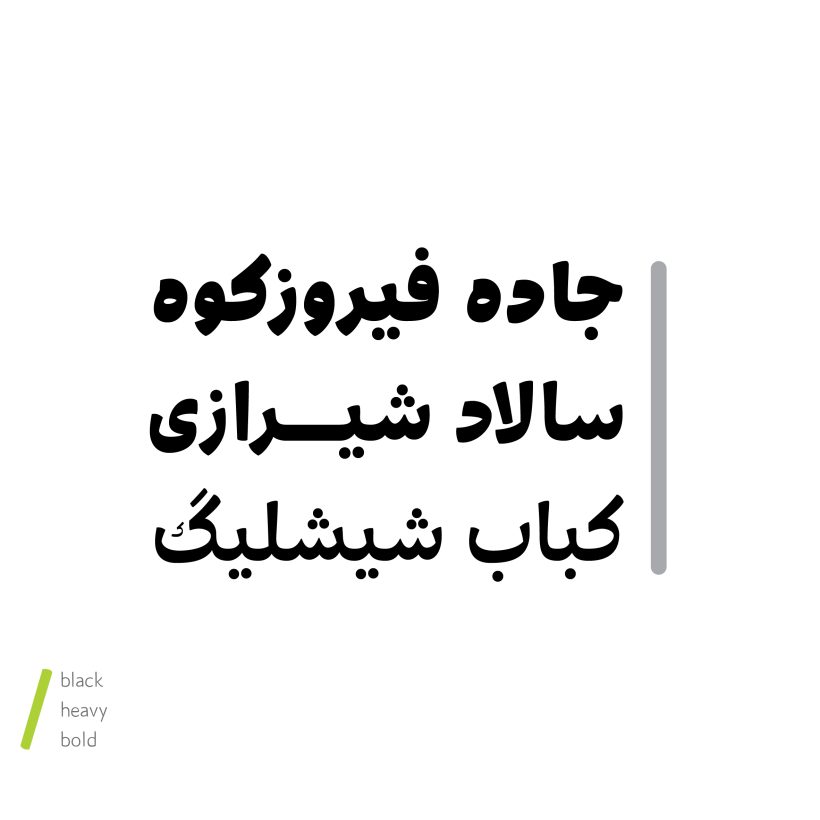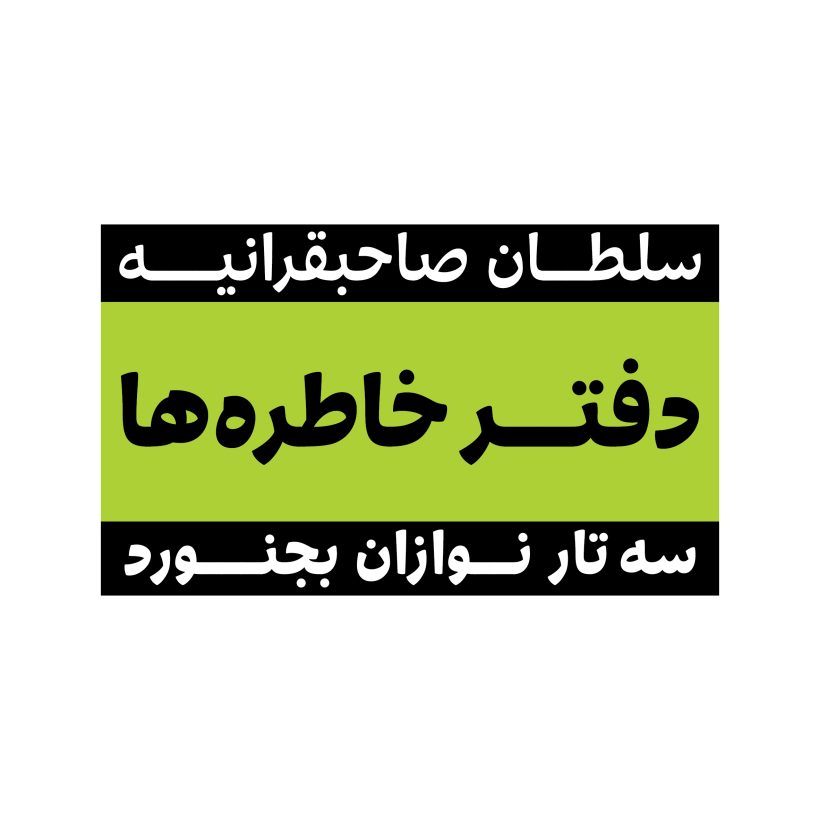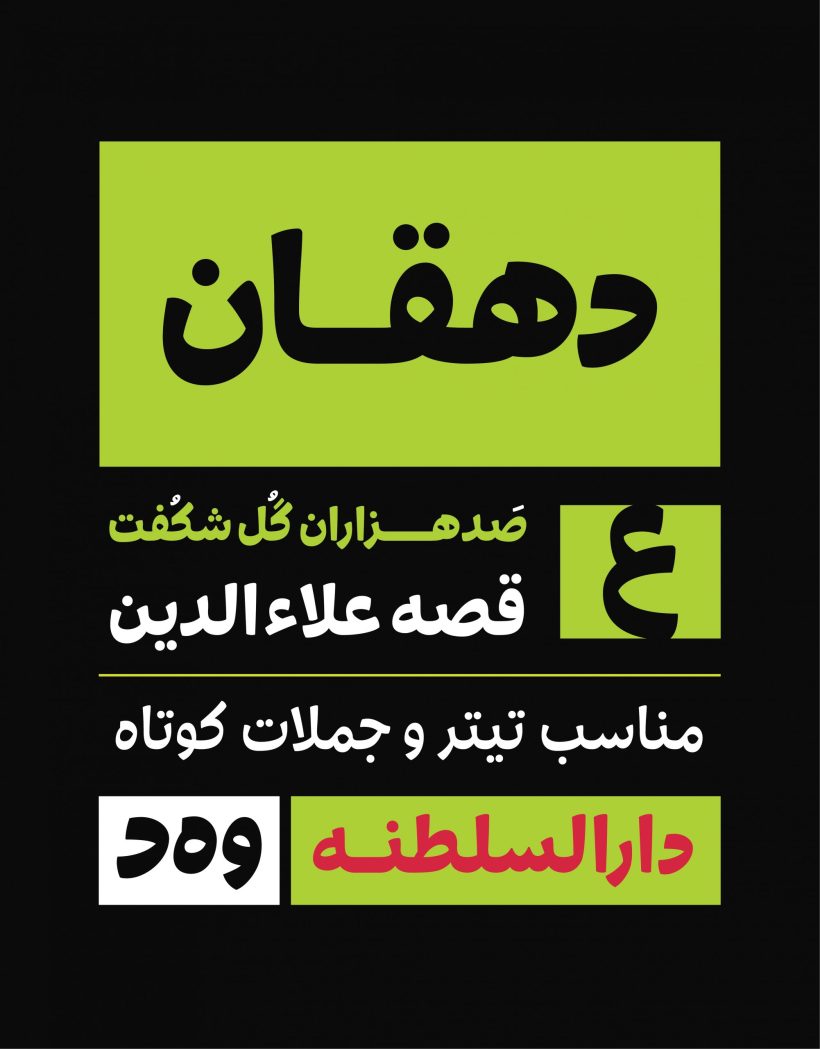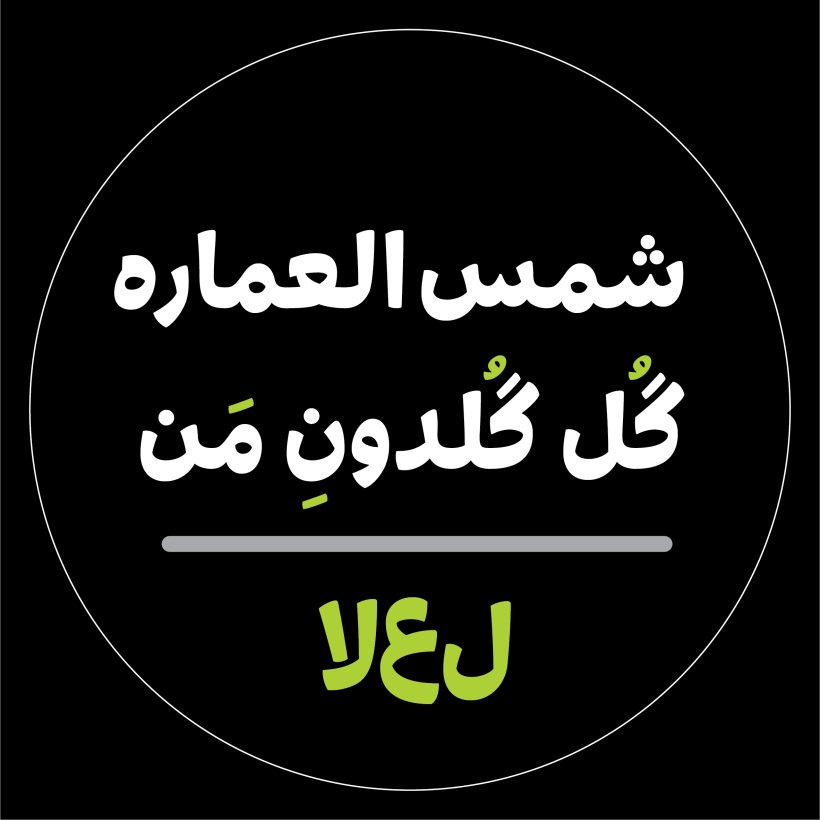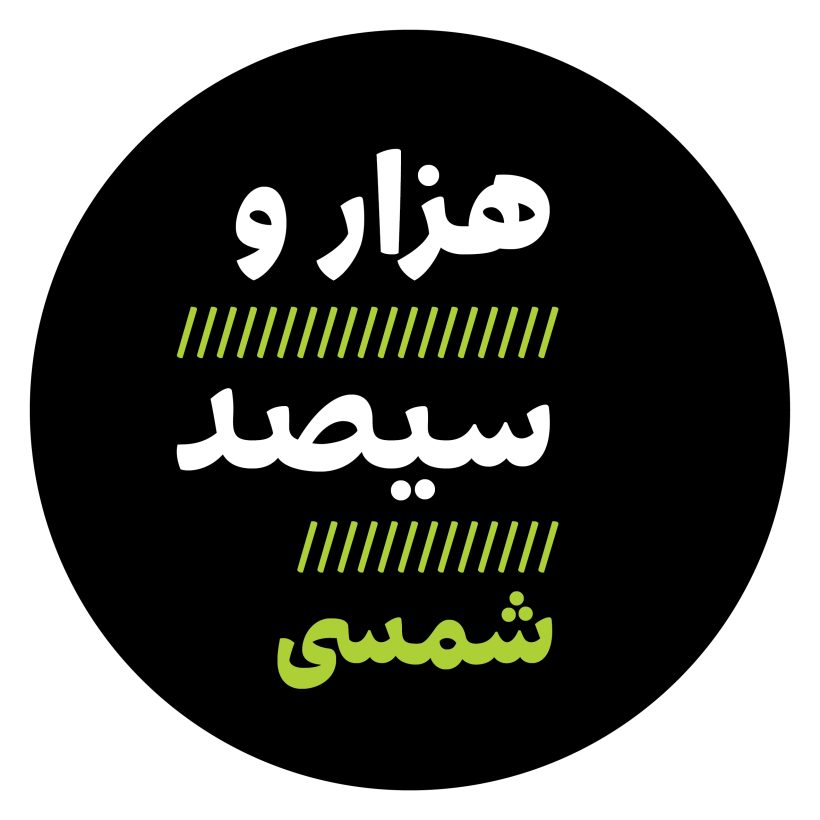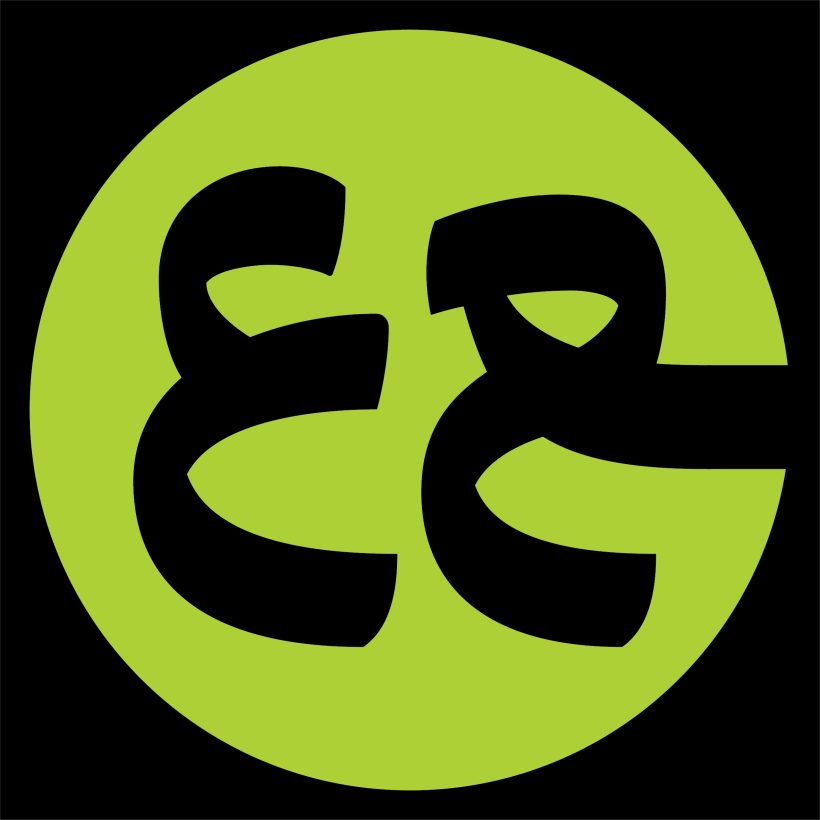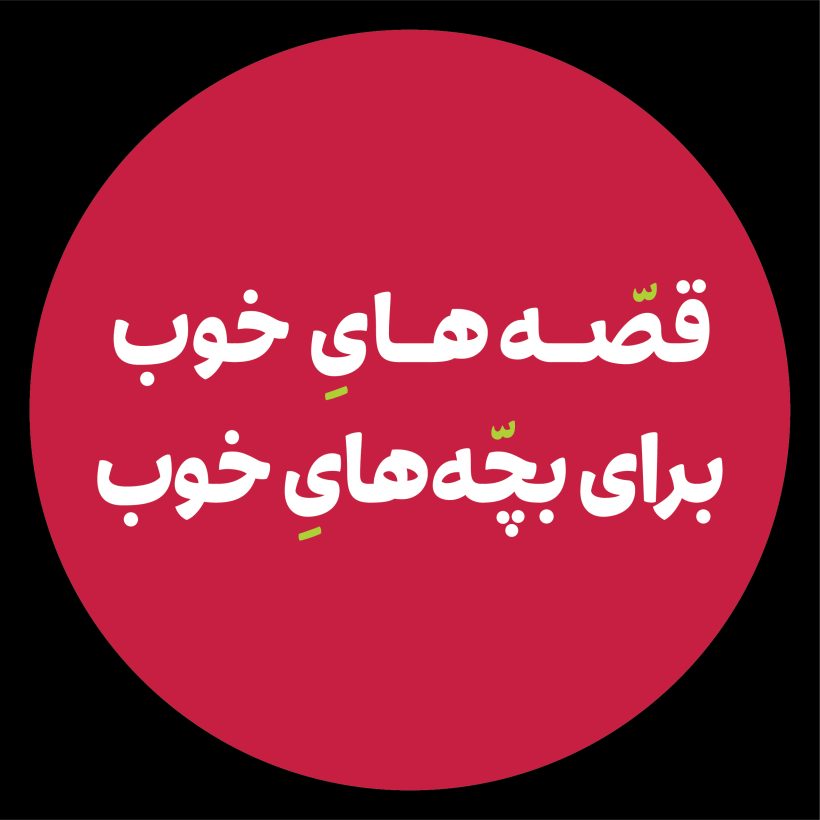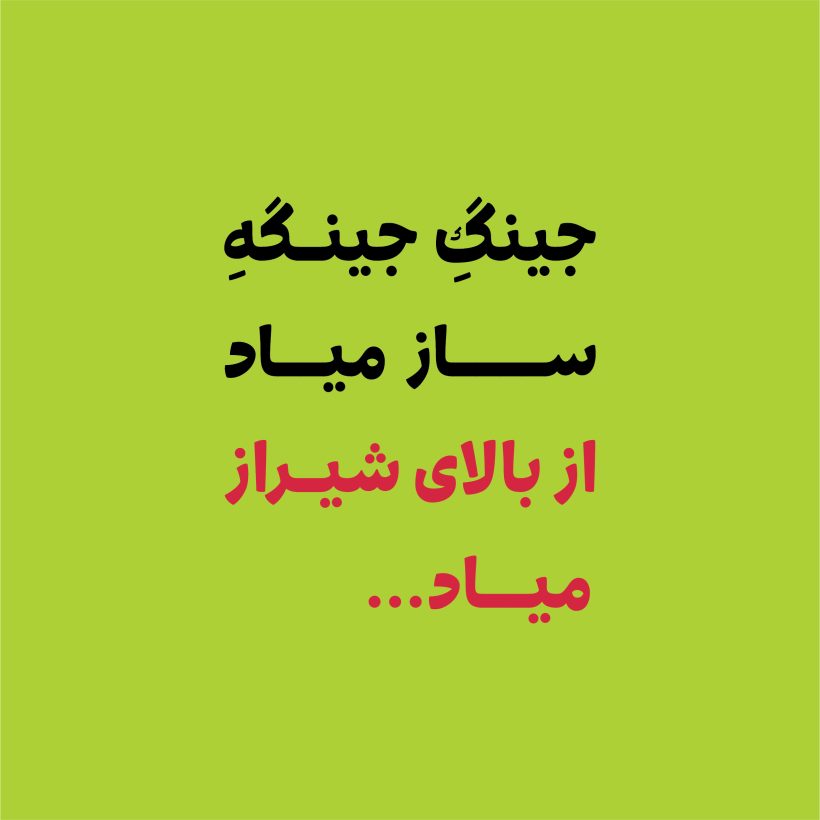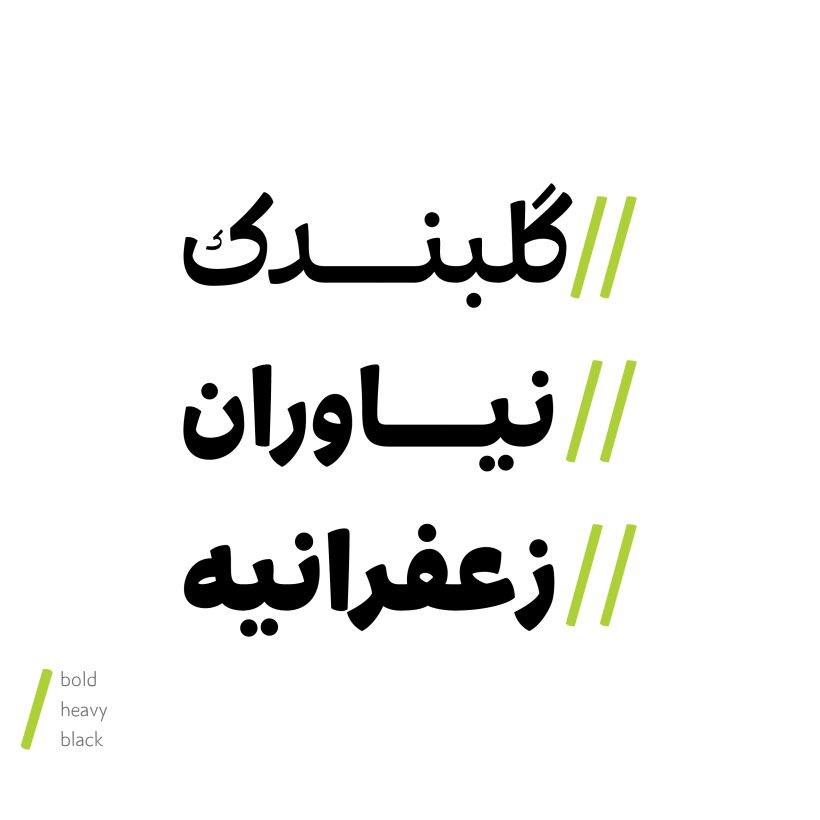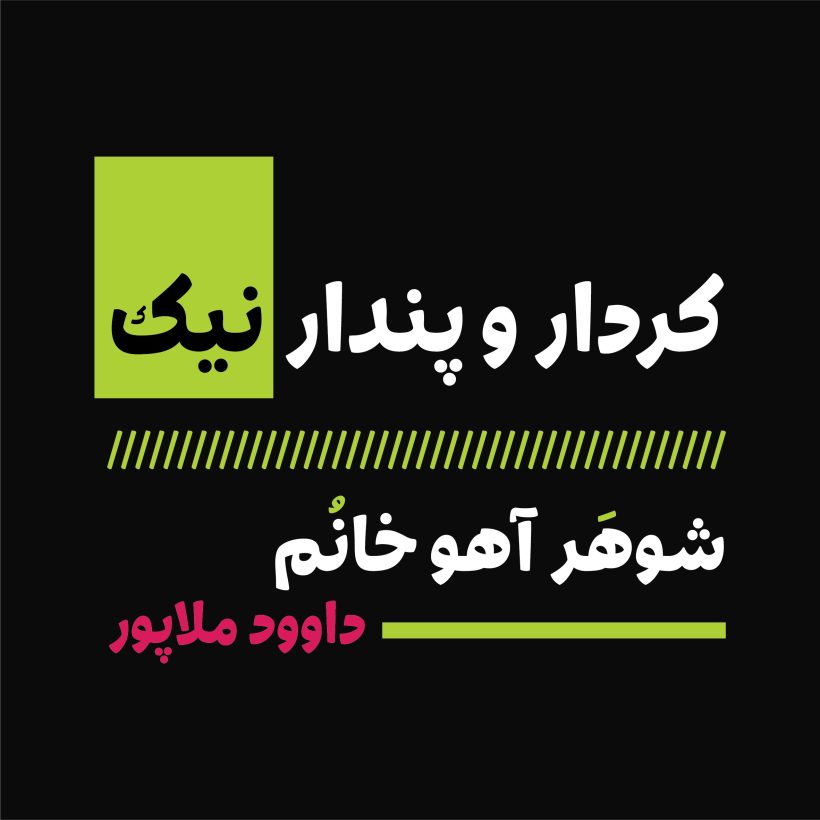
خانواده فونت دهقان
فونت دهقان با الهام از خط سکه های کهن و با لحنی صمیمی و عامیانه طراحی شده است.
دهقان فونت نمایشی، متمایز و در سه وزن bold / heavy / black طراحی و اجرا شده است. در این فونت حروف با دور بیشتری طراحی شده است و لحنی صمیمی و دوست داشتنی دارد و برای تولید محتوا و موضوعات و قصه های عامیانه مناسب به نظر می رسد.
در فونت دهقان قواعد کرنینگ و اعراب‌گذاری به طور کامل رعایت شده است. همچنین دهقان دارای لیگیچر و کاراکترهای جایگزین می‌باشد و این امکان را به مخاطب می‌دهد تا متناسب با نیازش، گزینه و فرم مناسب را انتخاب نماید.
اعداد فارسی و عربی در فونت دهقان تنظیم شده و قابل استفاده است.
فونت دهقان توسط معصومه مصلح در سال 1402 طراحی شده است.